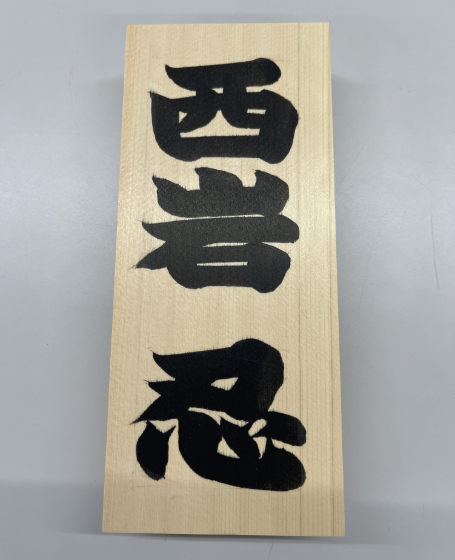
相扑文字(すもうもじ) 是一种独特的日本艺术文字。
这种字体的设计非常特别,它从相扑运动中汲取灵感,将相扑斗士在比赛中缠斗的状态融入到文字形态中,所以文字的内部几乎没有空隙,形象的表达出在相扑运动中运动员的争斗,也有希望会场能挤满观众的寓意。多用于相扑广告、节目表中。
相扑字是在根岸兼吉(三河屋)的书写下诞生的,所以这个字体也被称为“根岸流”。相扑文字虽然也是用特粗毛笔书写,但是笔画粗直有力。文字字形体现出相扑运动员的力量感,用苍劲有力的笔画书写出了一个独特的世界。